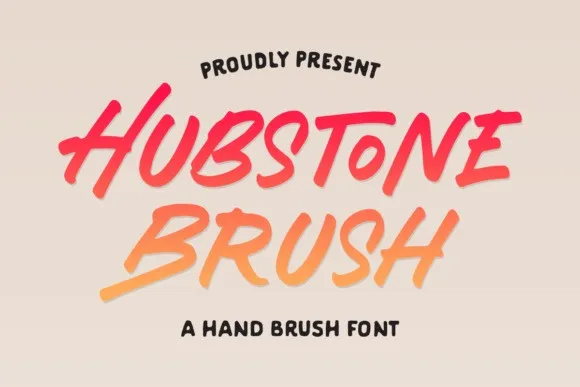
Hubstone Font – Download Grátis
A Hubstone Font é uma seleção elegante para designers que buscam um estilo fluído e versátil para seus projetos digitais. Criada na 99designs, essa tipografia script é ideal para aqueles buscando algo moderno e expressivo. Com traços fluidos e detalhes cuidadosamente preservados, a Hubstone oferece uma combinação chamativa entre maiúsculas e minúsculas maiúsculas. Além disso, a fonte vem com alternativas de letras, permitindo flexibilidade na criação de logotipos ou em qualquer outro formato formal, como convites, rótulos, logos, revistas, livros, cartões de boas-vindas, embalagens, moda, maquiagem, material de escritório e literatura, para citar apenas alguns exemplos. A Hubstone é perfeita para atender a um grande range de propósitos promocionais, garantindo que sua identidade visual seja chamativa e impecável em qualquer uso.